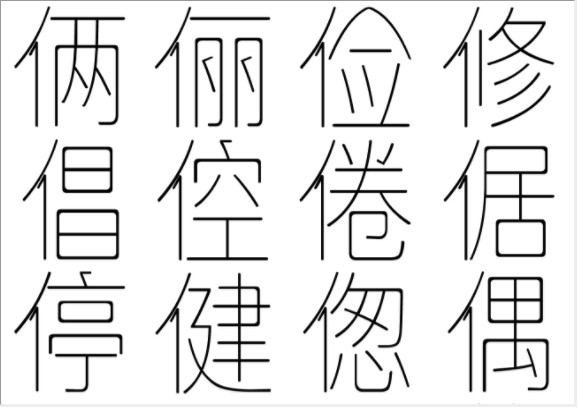
作品设计背景与理念
逐浪细阁体是一种基于现代汉字简体设计的字体,整个字体拥有以下特征:
纤细偏长:整体上比市面上的字体更加纤细,以下为对比市面常用字体效果:
严谨扑实:剔除字体中的花边和类明体中的衬线,使之在高分辨视野和户外识别性高。
折笔如阁:笔画中多有扎笔,一般每字一处折笔,使之如古之阁楼、汉之花窗,略呈红楼之美,尽享古韵丰姿。
而对于人字头等处理,则采用了苍穹式的设计,使之感觉圆润。
作品使用范围
文本装潢、信息展示、数据制作、装潢设计、计算艺术设计、视觉设计、字帖等一切合法应用场景。
本款“逐浪细阁体”是一款书写很新颖的字体,字体大方,适合各种设计作品使用!欢迎下载!